وبسایت فونت ایران در کنار فونتهای حرفهای و تجاری، مجموعهای ارزشمند از فونتهای فارسی رایگان را در اختیار طراحان، دانشجویان و علاقهمندان تایپوگرافی قرار داده است. این فونتها اغلب در قالب پروژههای دانشجویی و تحت نظارت اساتید طراحی حروف شکل گرفتهاند و از نظر ساختار و اجرا، کیفیتی فراتر از فونتهای رایگان معمول دارند.
1. خانواده فونت ایران
قلم ایران ترکیبی است از طراحی حروف معاصر و حالوهوای فونتهای آشنای ایرانی مانند زر، نازنین و میترا. این فونت بهگونهای طراحی شده که در نگاه اول برای مخاطب ناآشنا به نظر نمیرسد؛ ویژگیای که برای فونتهای متنی یک مزیت مهم محسوب میشود. خوانایی بالا، نظم بهتر سطر و ستون و طراحی یکدستتر، قلم ایران را به گزینهای مناسب برای مطبوعات و متون طولانی تبدیل کرده است.
- این تایپفیس در قالب پروژه فونت فرهنگ بهروزرسانی شده است.
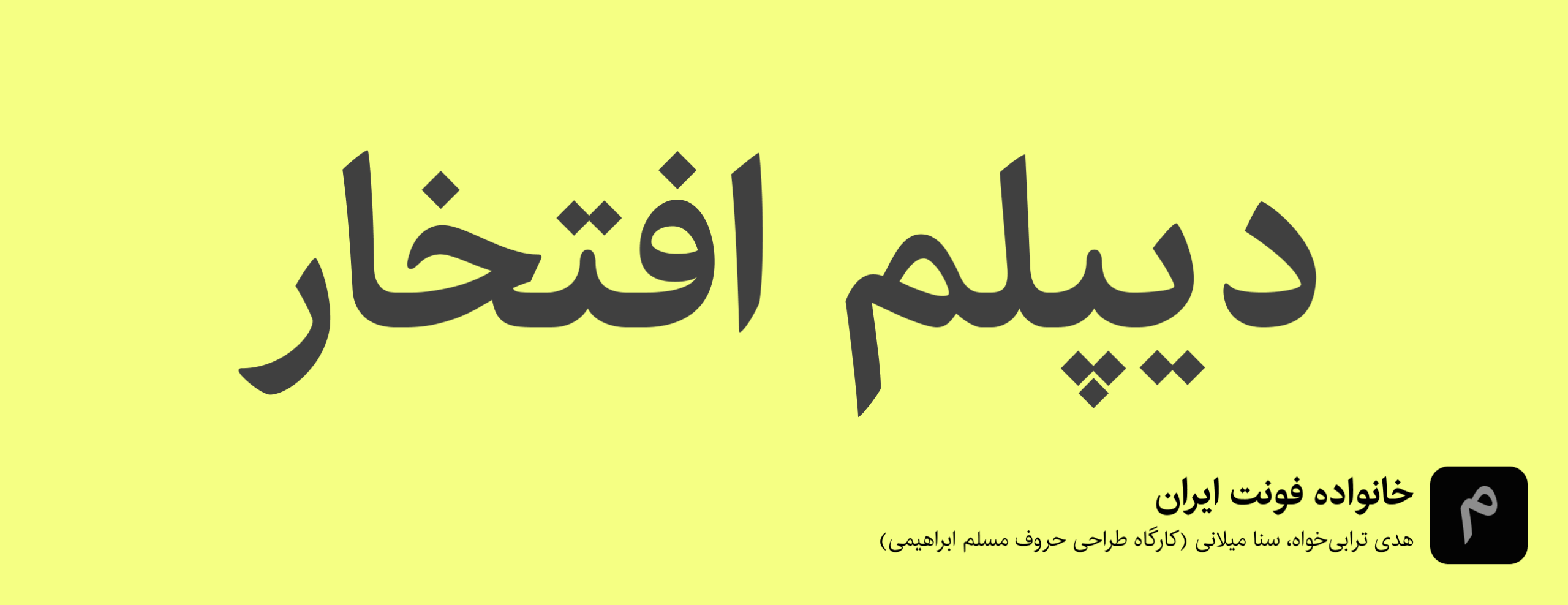
2. فونت ایران گرد
نسخهای بولد و مدور از فونت ایران که با لبههای نرم و نقطههای دایرهای، ظاهری فانتزی و اصطلاحاً «پفکی» دارد. این فونت برای تبلیغات، بستهبندی مواد غذایی، کودک و نوجوان و طراحیهای غیررسمی بسیار مناسب است.
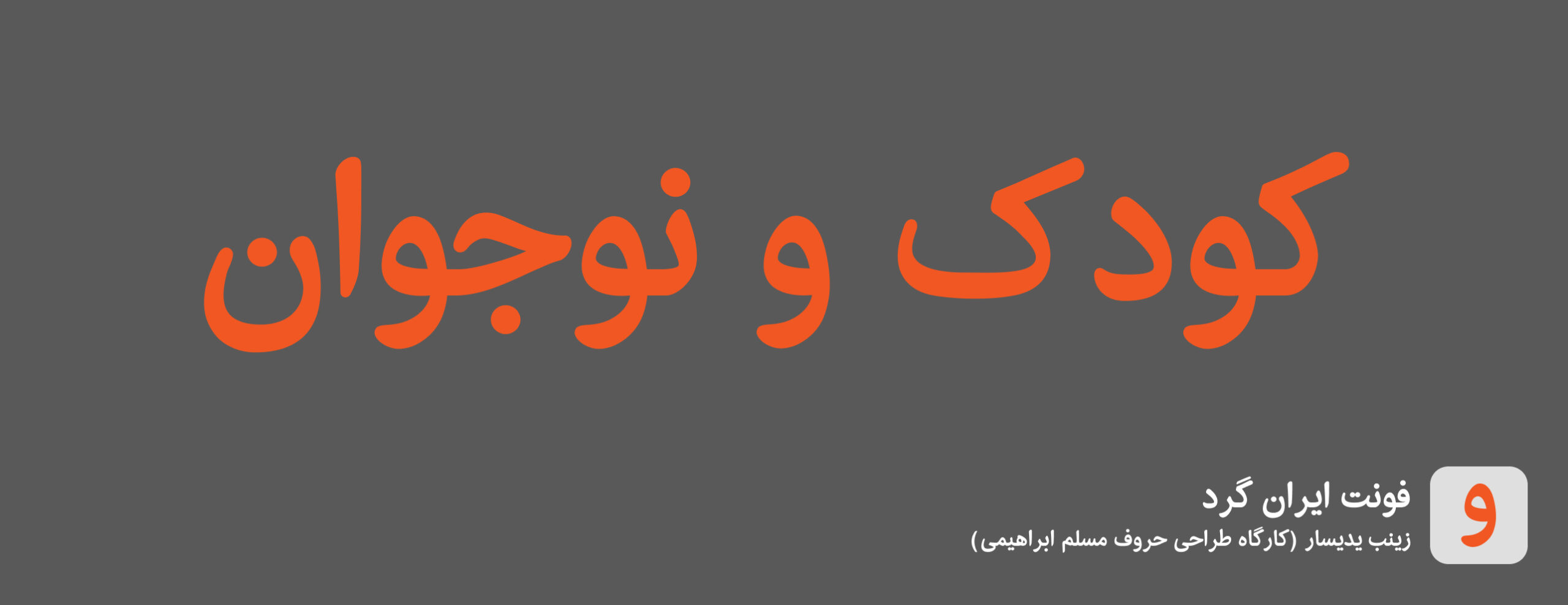
3. فونت رویین (Rooyin Free)
فونت رویین تلاشی موفق در طراحی فونت پیکسلی فارسی است. نسخه رایگان این فونت به صورت کاملاً پیکسلی طراحی شده و برای پیکسلآرت، بازیها و نمایشگرهای با رزولوشن پایین گزینهای عالی محسوب میشود.
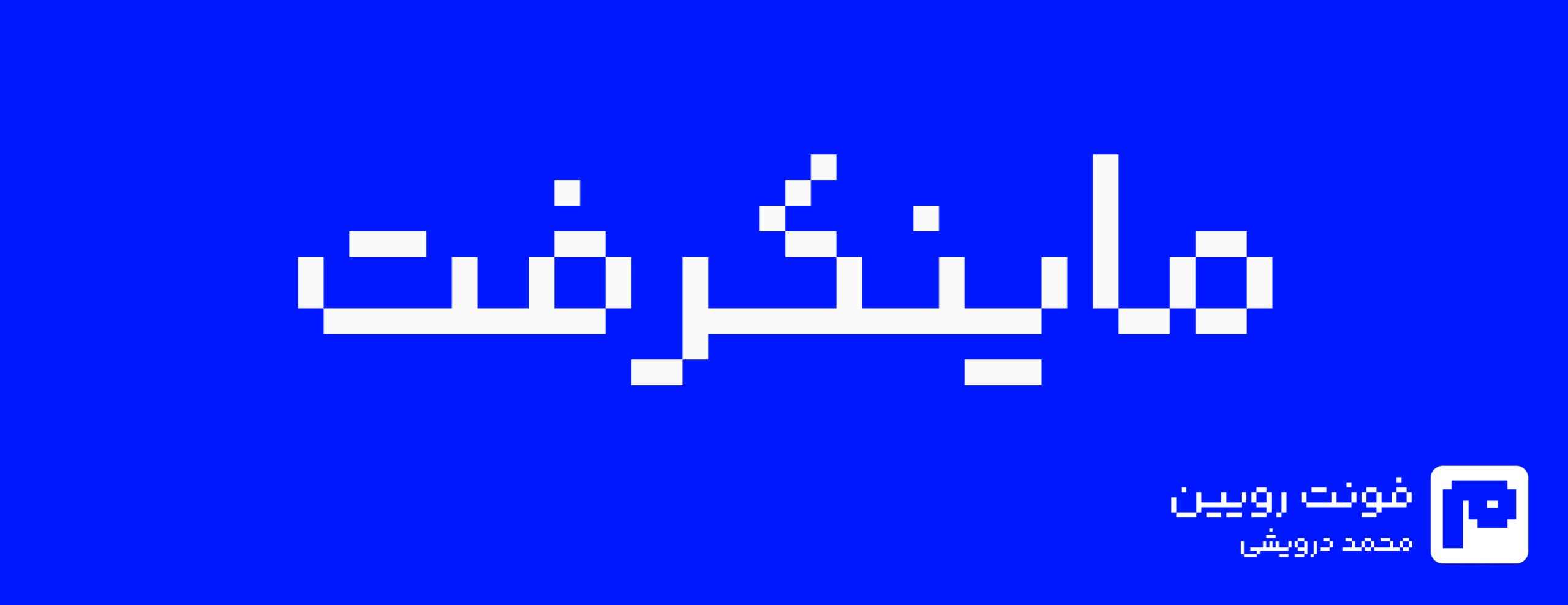
4. فونت محبوبه مهرآور
فونتی دستنویس با ساختاری کنترلشده که توسط محبوبه مهرآور و با ایده نوشتن حروف بهجای قلم، با چوب گوشپاککن طراحی شده است. این فونت با وجود حس غیررسمی، خوانایی خوبی دارد و برای طراحیهایی که به حس انسانی و صمیمی نیاز دارند، انتخاب مناسبی است.
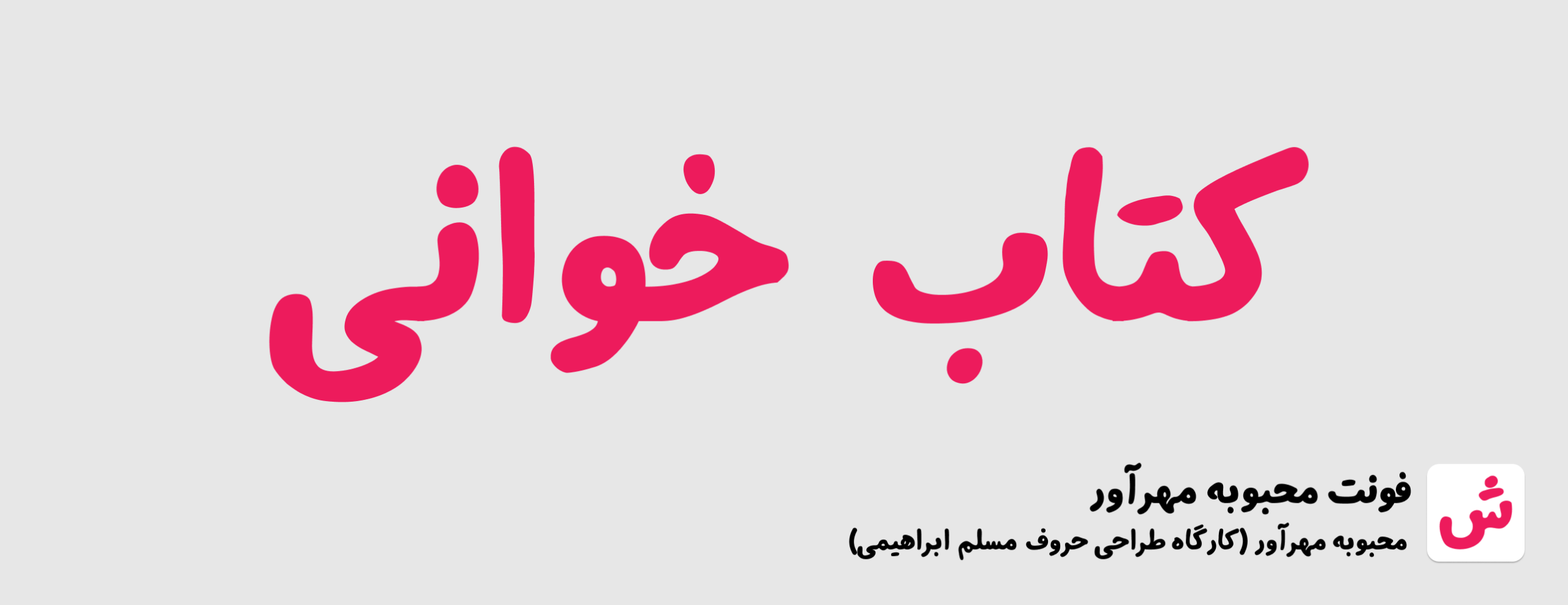
5. فونت روستا
فونت روستا یک قلم تیتر فانتزی با حالوهوای کودکانه و عامیانه است که حروف آن بهصورت آزاد و دستی طراحی شدهاند. این فونت برای موضوعات طنز، کودک و نوجوان، فرهنگ عامه و طراحیهای غیررسمی کاربرد فراوانی دارد و میتواند جایگزینی خلاقانه برای فونت تیتر کلاسیک باشد.
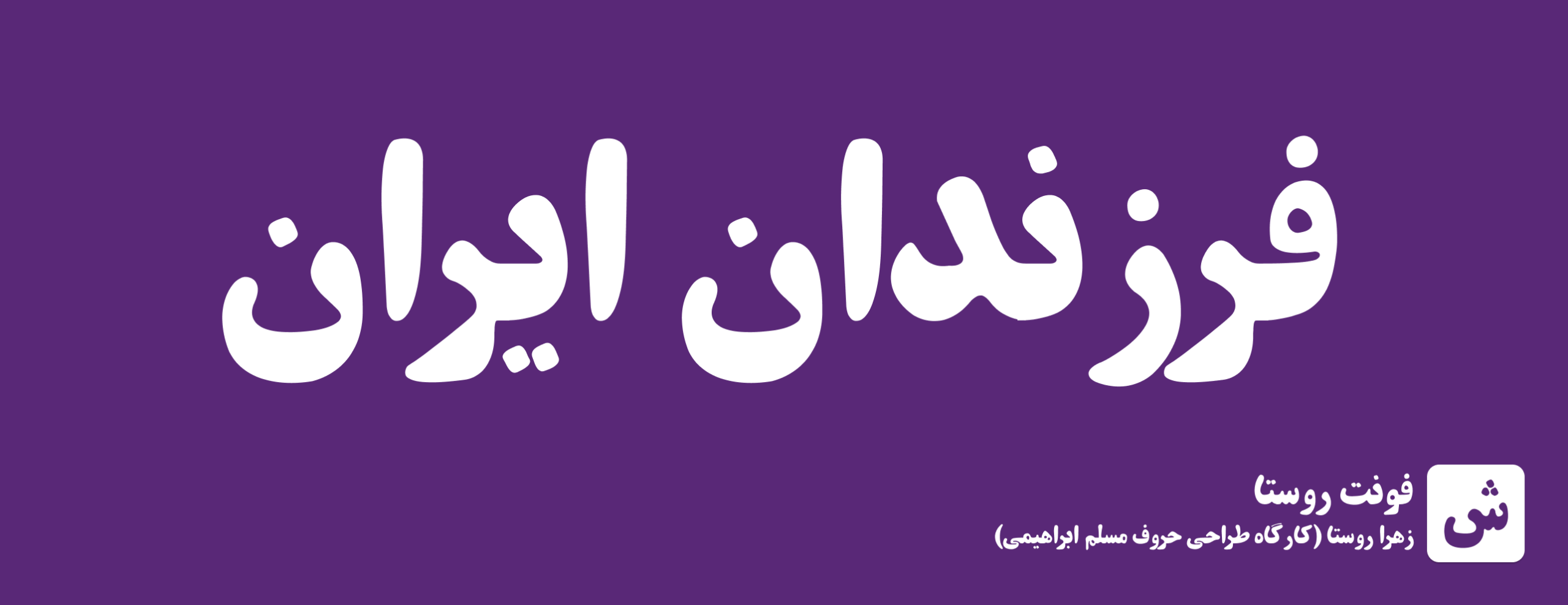
6. فونت هدی
فونت هدی یک فونت فانتزی است که با تغییرات اغراقآمیز در ساختار فونتهای نسخ ایرانی، شخصیتی جسور و متفاوت پیدا کرده است. این فونت در عین فانتزی بودن، همچنان حس جدیت و رسمیت را حفظ میکند و برای تایپوگرافیهای خاص انتخابی جذاب است.
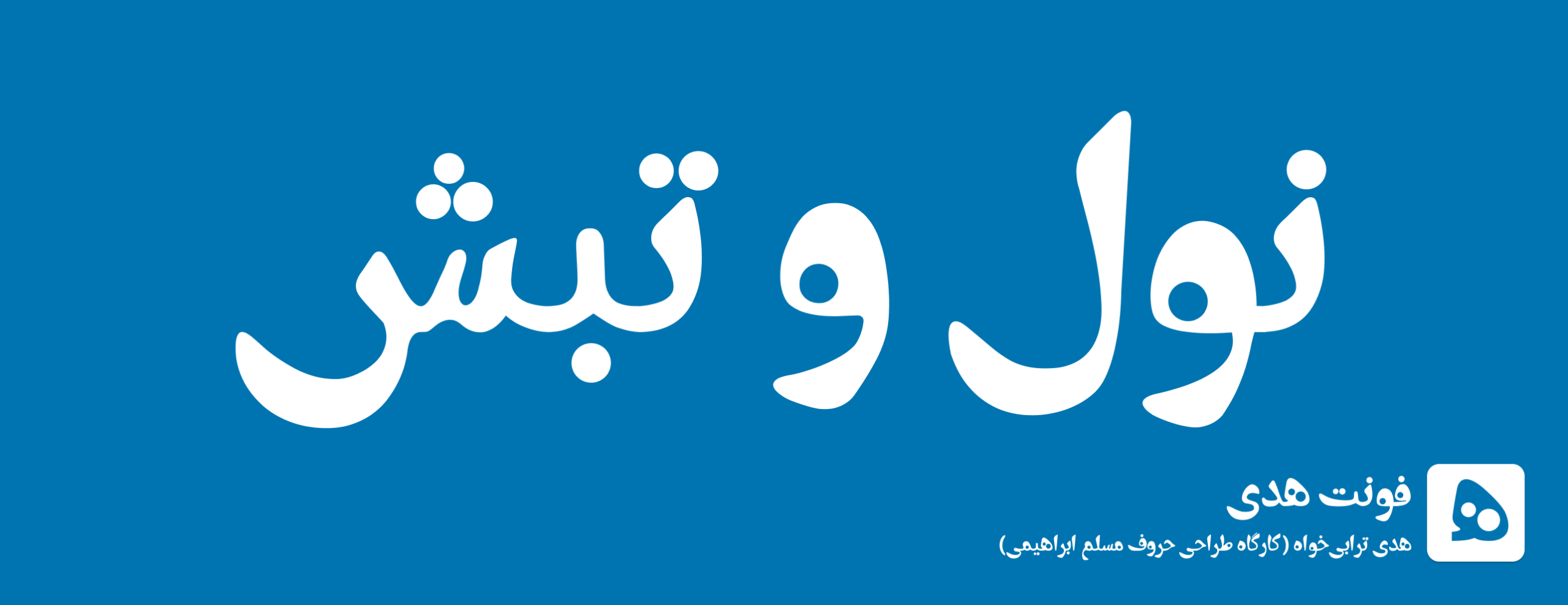
7. فونت کاموا
فونتی گرافیکی با ایدهای ساده و خلاقانه: حروفی که با نخ کاموا نوشته شدهاند. این فونت به همراه نسخه انگلیسی هماهنگ ارائه شده و برای طراحیهای تصویری، فانتزی و خاص بسیار کاربردی است.
8. فونت تیتر زبر
فونتی افکتیو که با ایجاد بافت و تغییر شکل روی فونت تیتر شکل گرفته و برای طراحیهای گرافیکی خاص و متفاوت کاربرد دارد.
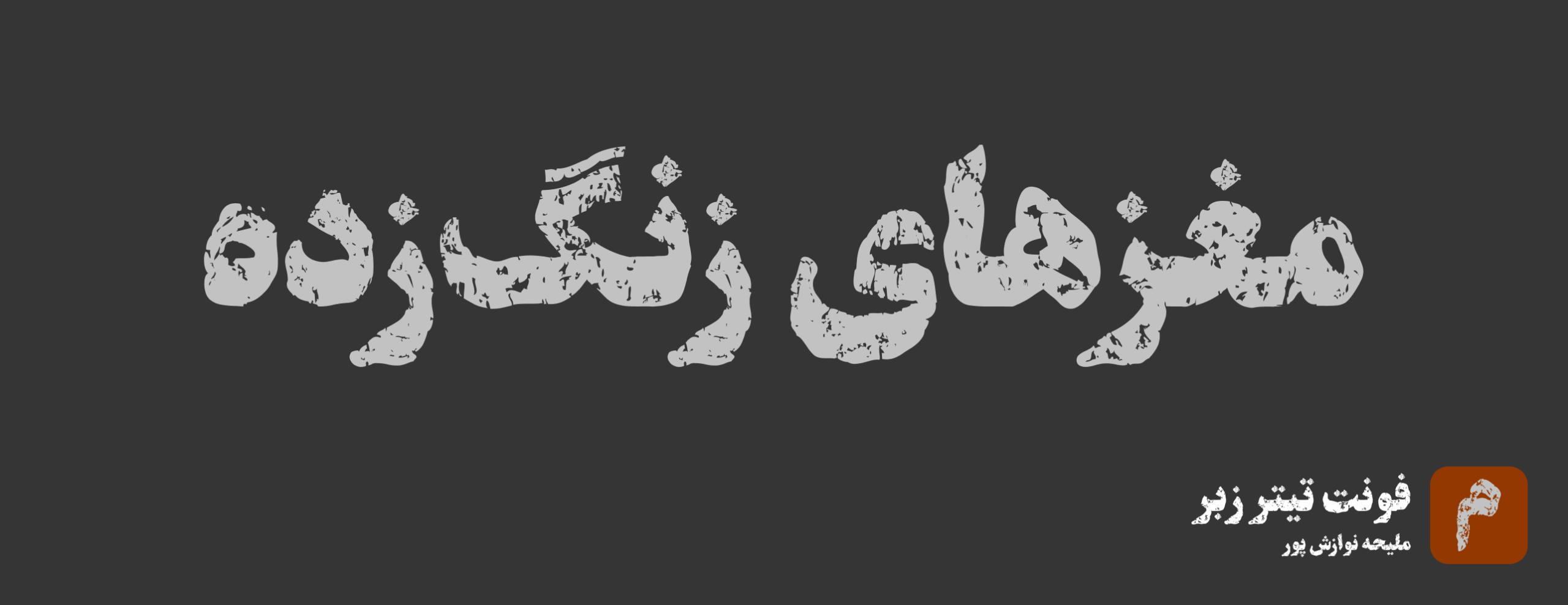
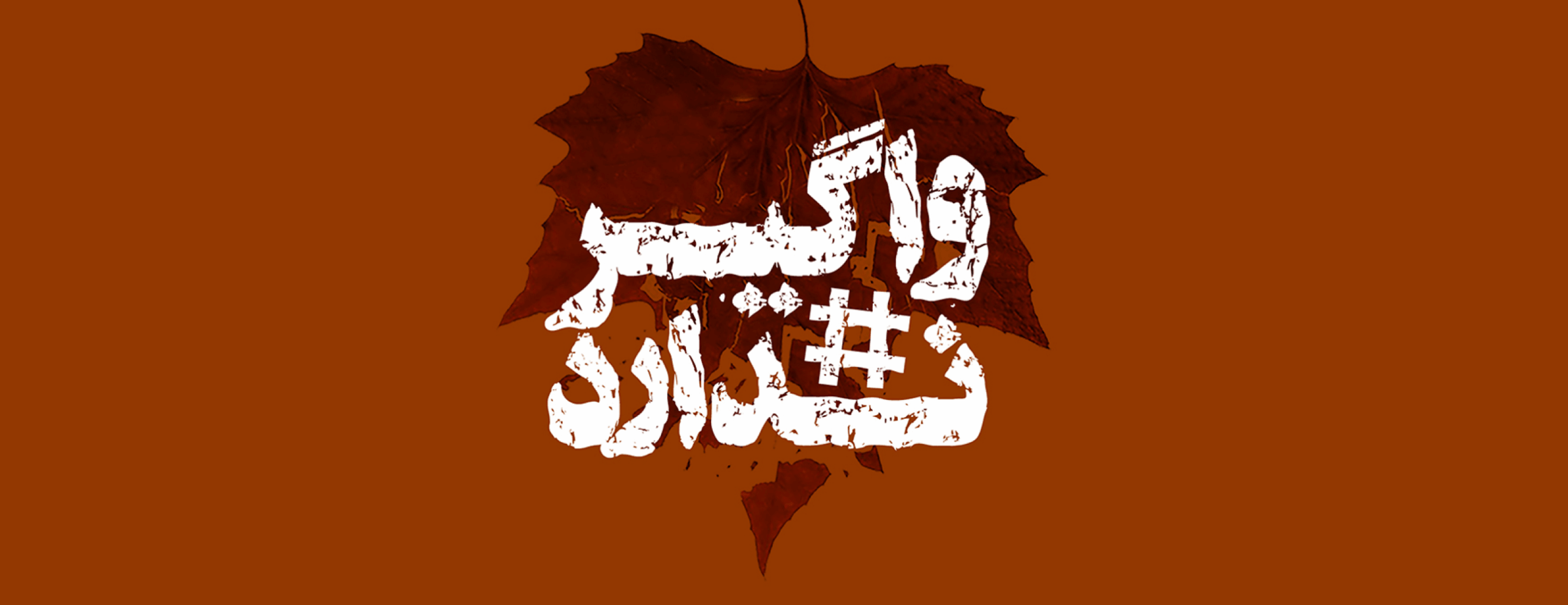
9. فونت ایران شارپ
ایران شارپ بازطراحی مدرنی از فونتهای کلاسیک ایرانی مانند زر و نازنین است. این فونت با حفظ روح آشنای قلمهای قدیمی، مشکلات فنی آنها را برطرف کرده و گزینهای ایدهآل برای طراحانی است که به تایپوگرافی متنی حساس هستند.
- این تایپفیس در قالب پروژه فونت فرهنگ بهروزرسانی شده است.
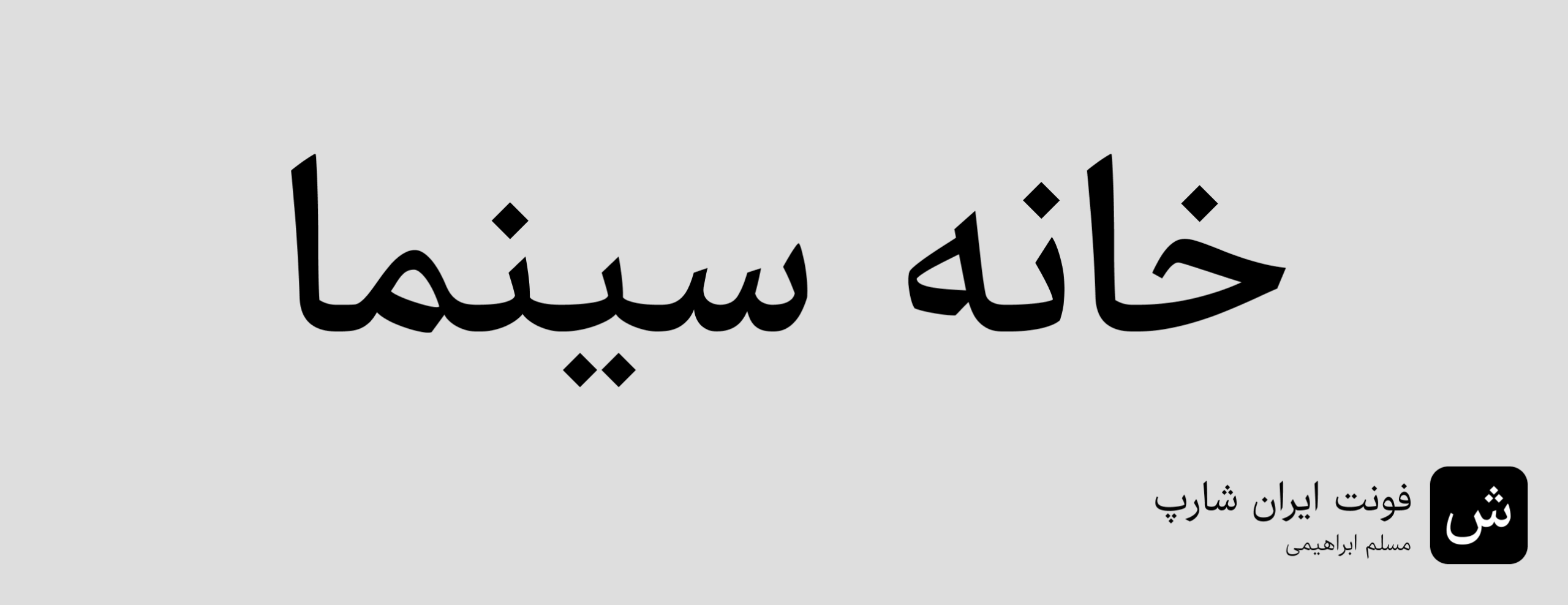
10. فونت ایران مارکر
نسخهای با حس انسانیتر از فونت ایران که با ایده بازنویسی حروف با ماژیک طراحی شده است. این فونت نه کاملاً دستنویس و نه کاملاً ماشینی است و تعادلی جذاب بین این دو ایجاد میکند.
11. فونت ایران درندیس
نسخهای تزئینی و گیاهی از فونت ایران که توسط سنا درندیس طراحی شده است. این فونت یک قلم گرافیکی با کاربرد خاص است و برای استفاده در اندازههای بزرگ مانند پوستر، جلد کتاب و بیلبورد بسیار مناسب است.
12. فونت ایران خوارزمی
ایران خوارزمی یک پروژه دانشجویی است که توسط سحر خوارزمی و زیر نظر مسلم ابراهیمی در سالهای ۱۳۹۲–۱۳۹۳ طراحی شده است. این فونت با الهام از ساختار فونت ایران، تلاشی برای خلق یک قلم سنگین با حداقل اختلاف ضخامت در ضعف و قوتهاست. حذف برشهای نوکتیز و گرد و توجه به تعادل فضای مثبت و منفی، از ویژگیهای شاخص این فونت محسوب میشود.